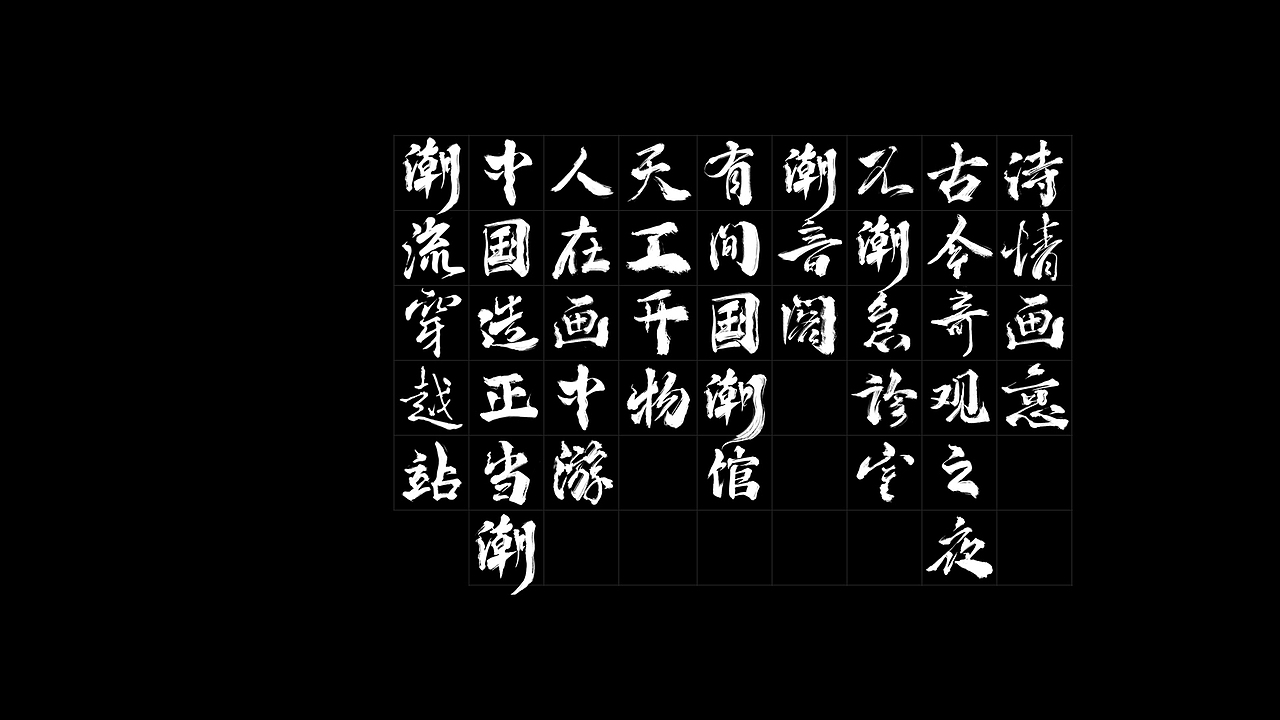
人民日报新媒体【有间国潮馆】创意设计
5月10日—12日,人民日报新媒体在北京三里屯设置的“国潮”主题创意体验馆,现已圆满收官。有幸继时光博物馆之后,再次担任本次活动的主视觉设计,现将一部分设计稿及现场照片存于此处,以供留存。
活动主视觉,意图将中国传统元素和潮元素相互融合,使其具有趣味性且贴合活动主题。
活动主视觉(横版)
活动的主题logo
为本次活动设计的部分字体